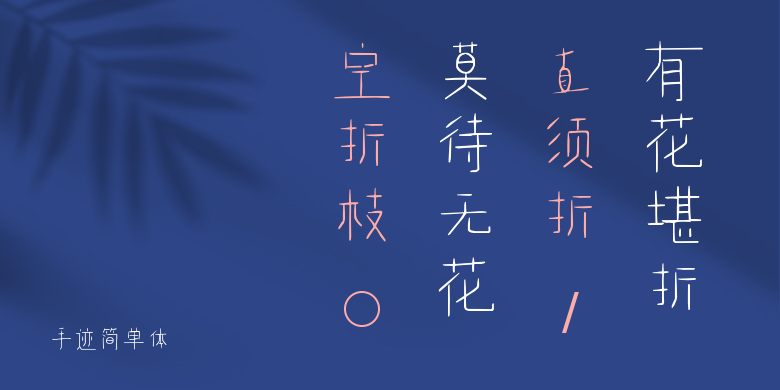
手迹简单体
手迹简单体,这款字体结构工整、笔画清晰,兼顾美观与易读性,适用于标题、正文、海报、包装、LOGO 等多种场景。字形优雅稳定,风格百搭耐看,适配日常排版与创意设计,让文字呈现更舒适、更具质感。手迹简单体一笔一画,皆是细节,以均衡的比例、流畅的线条打造舒适视觉体验,字形端正大气,风格简约现代。无论是商业设计、品牌宣传还是日常排版,都能轻松驾驭,让文字更有格调与力量。手迹简单体字体下载。